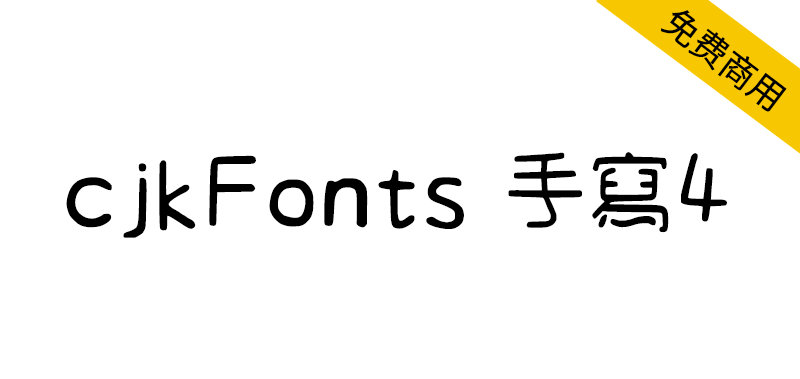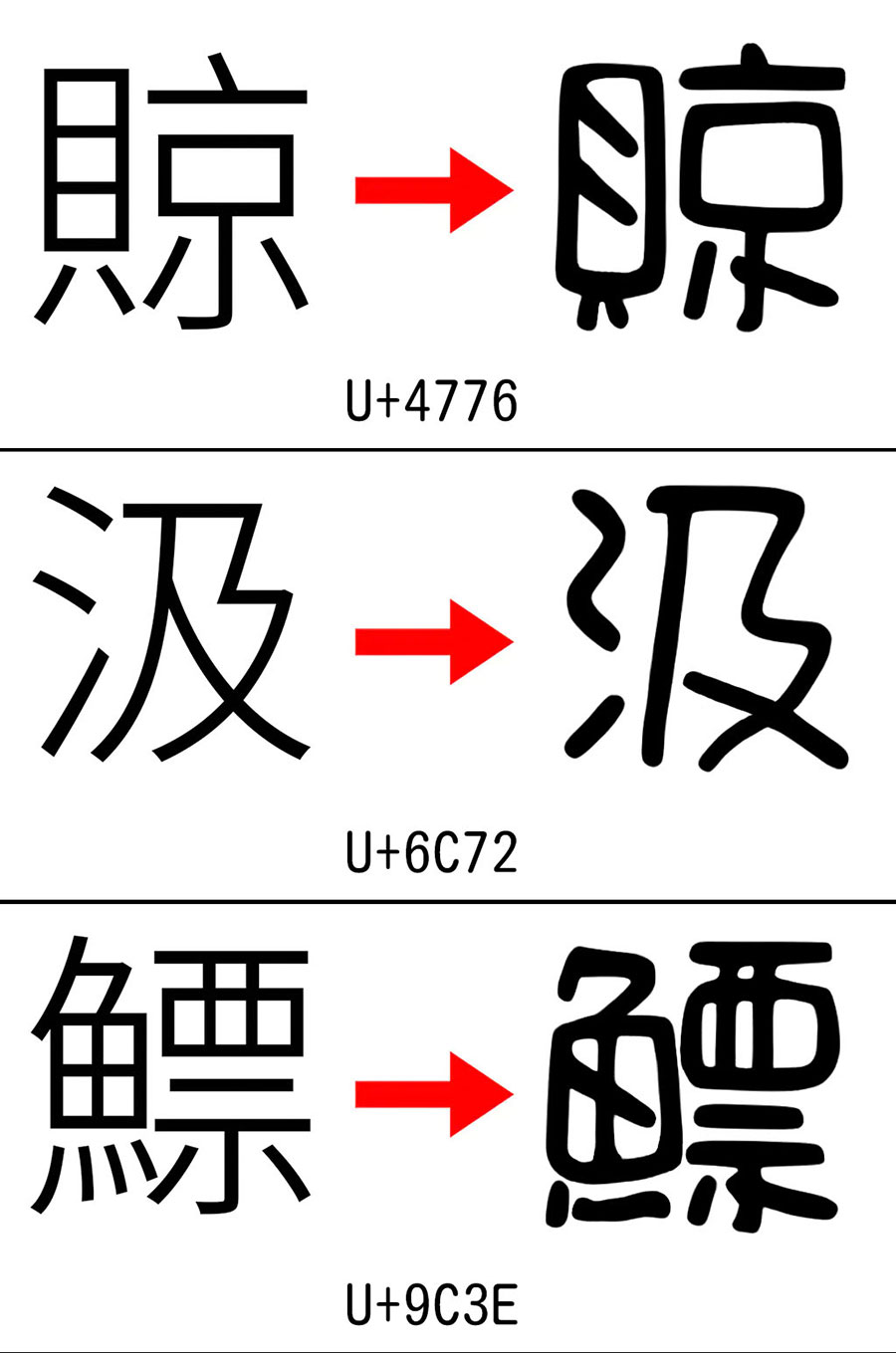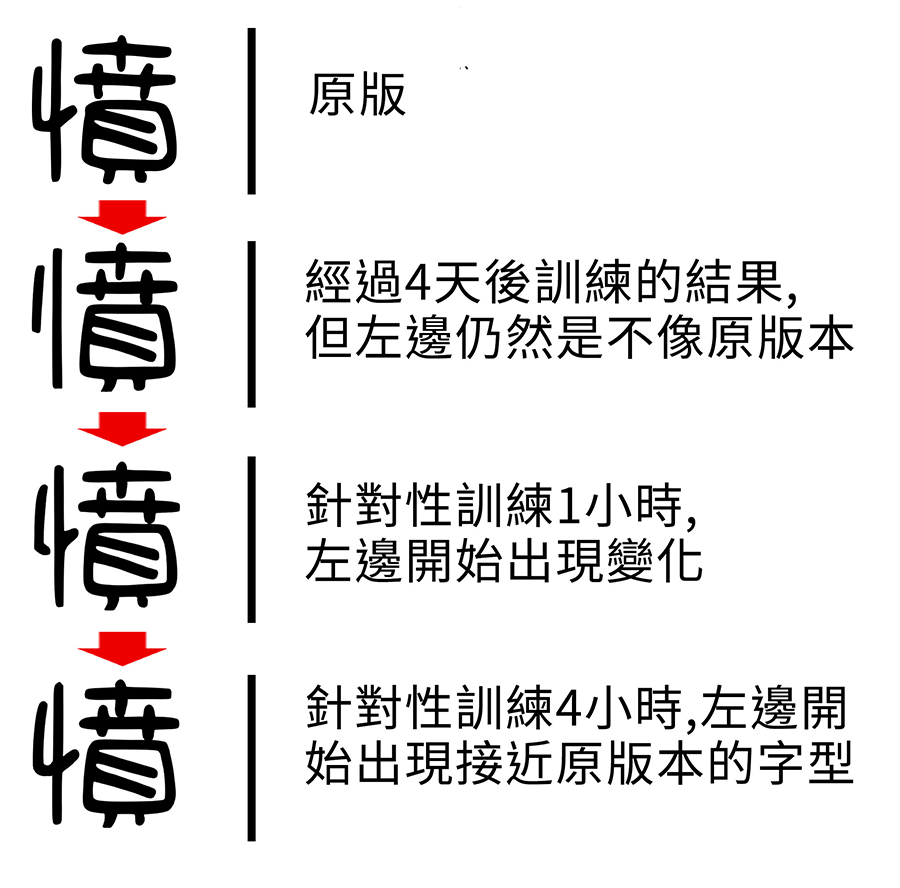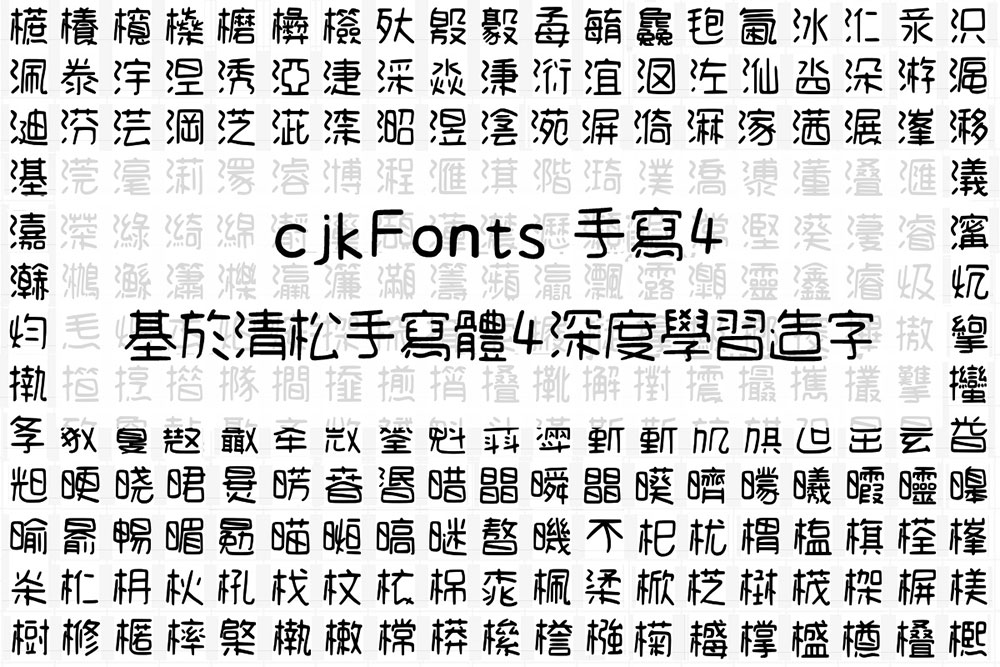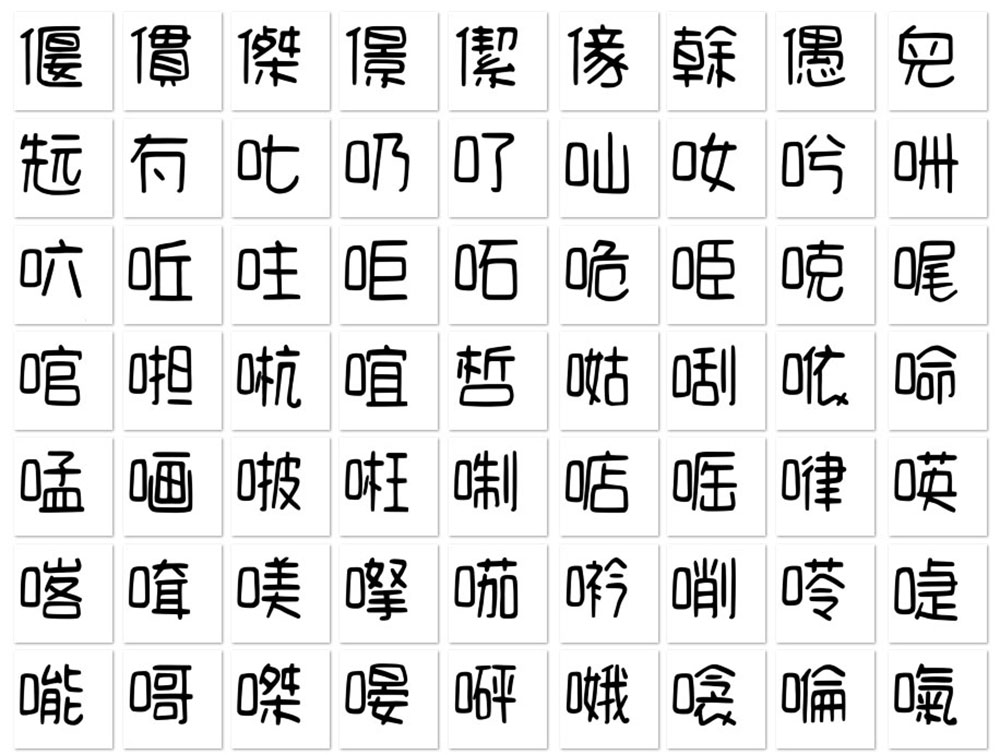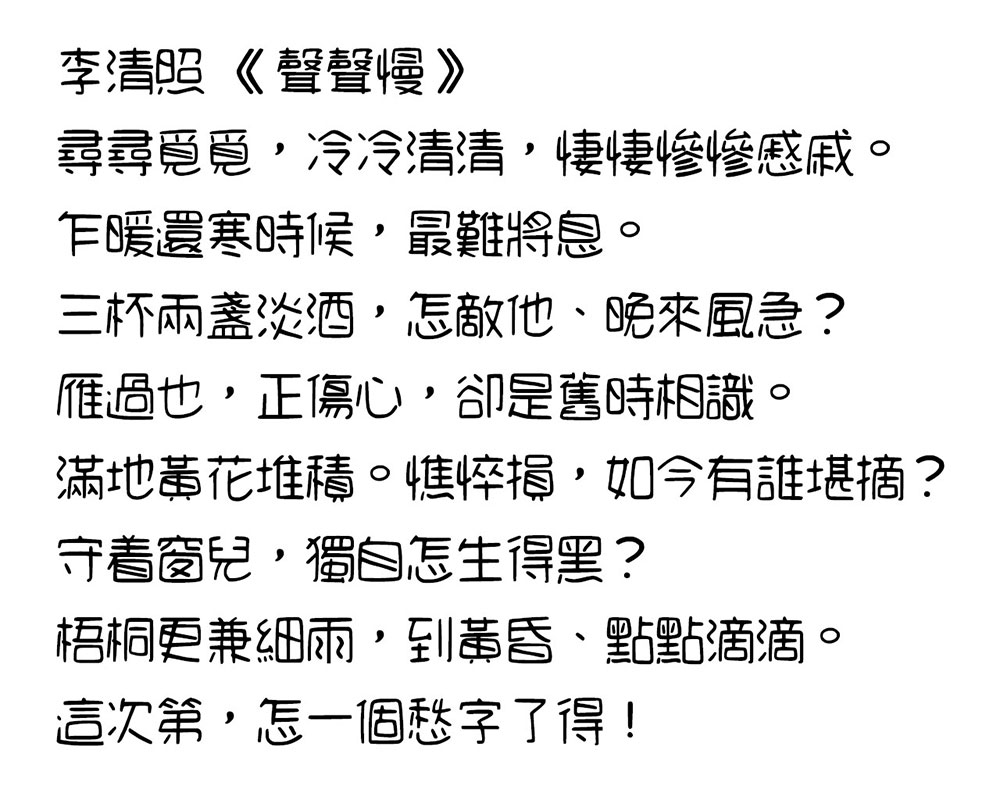
cjkFonts手写4是基于清松手写体4透过AI深度学习造字,原本清松手写体4大约有4千几百字,使用AI已造了2万7千字,但因为要时间后期制作,现在只释出大约1万2千字,其余的字待有时间才再加入。
由于是电脑学习了字体的特点及风格后,每个字根据学习后的数据造字,所以字体的风格会跟清松手写体4有轻微的分别。
今次是1万2千字的版本,大约用了2个月时间完成制作。清松手写体4的风格跟一般字变化比较大,在整过训练过程中,要反复检视结果,然后再训练,再检视,直至大部份的字体跟原版接近才能开始后期制作。